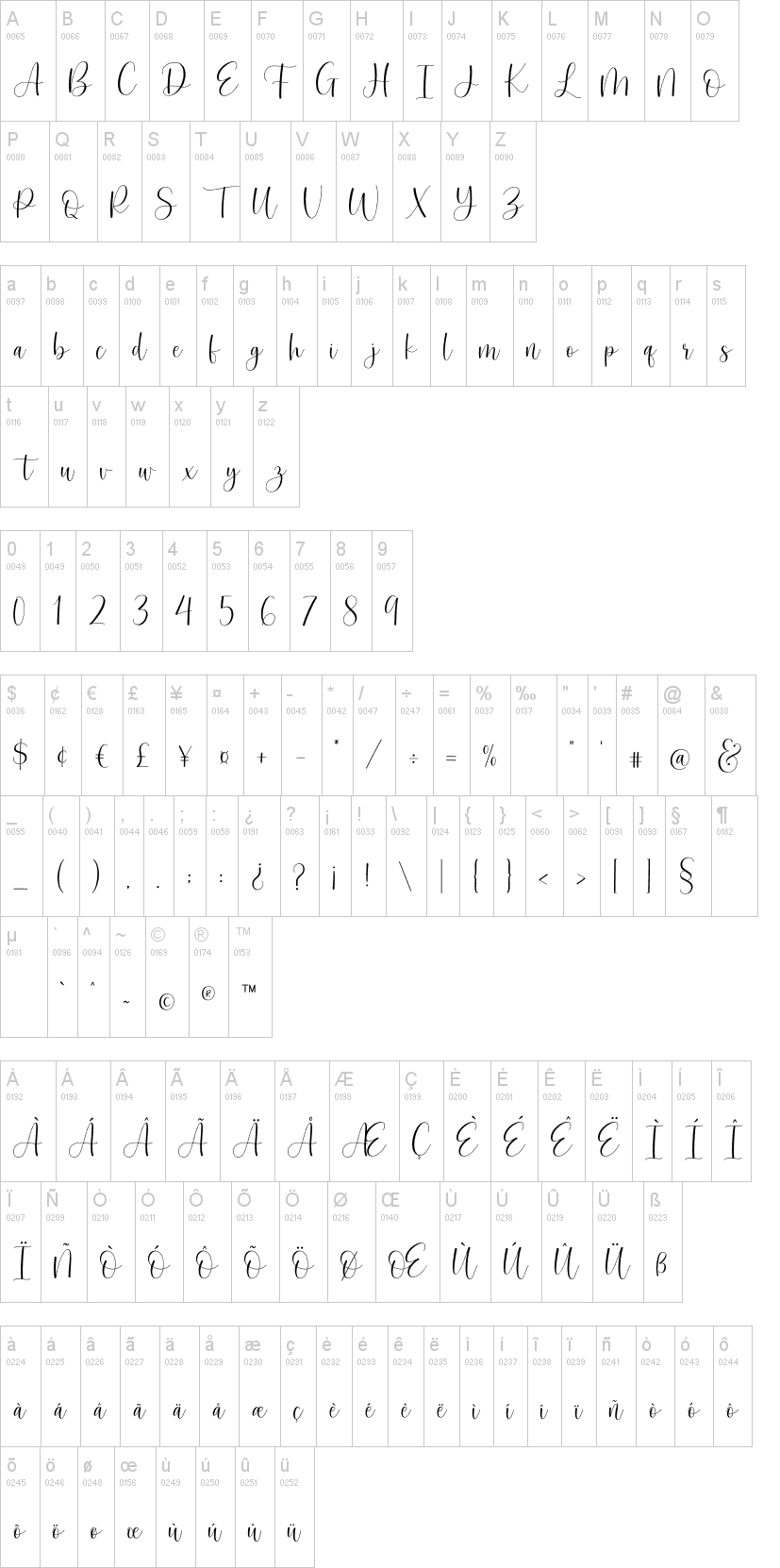
Hernitta
Hernitta 是一款简约、现代的英文字体,它的特点是拥有细腻的轮廓,清晰的笔画,柔和的曲线,以及清新的字体风格。它可以用于商业、广告、品牌标识、网页设计、印刷品等多种场合。Hernitta 字体可以帮助您建立一个简单而有效的设计,从而让您的作品更具吸引力和识别度。
Hernitta是一款非常不错的手写艺术字体,具有很好的视觉感,适合于文化类的宣传设计、商业类品牌的广告和产品包装设计以及个性化文字排版等较多场景。